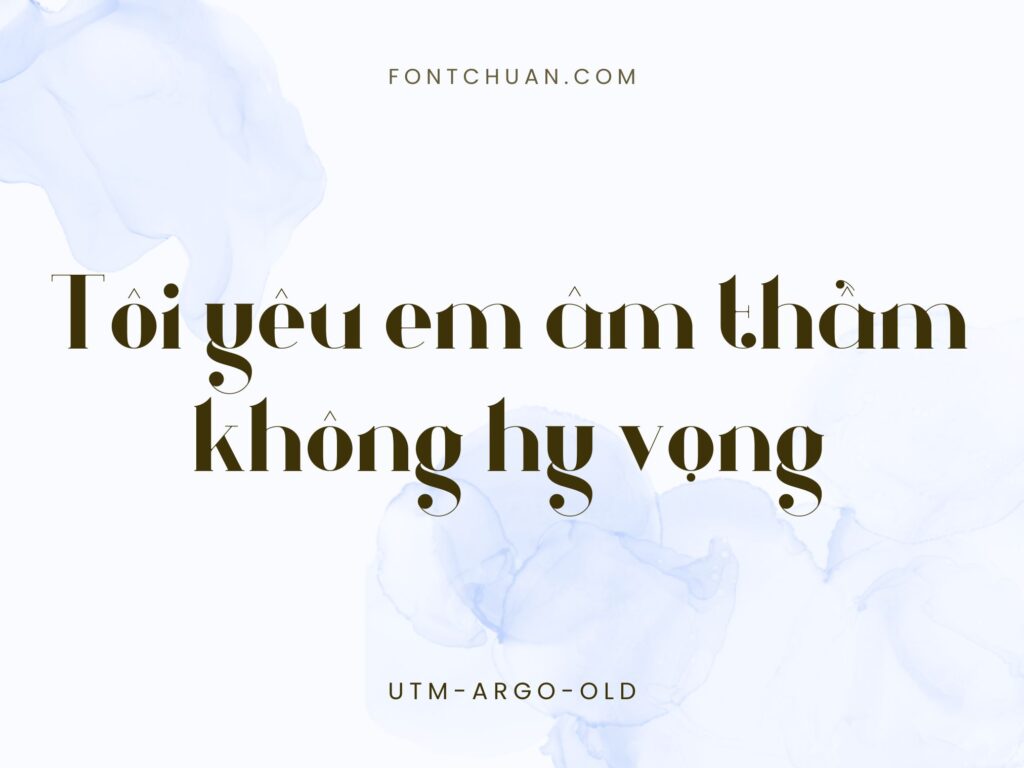
Font UTM Argo Old Việt Hóa
UTM Argo Old là một Font Serif mang phong cách cổ điển và thuộc dòng Font Vintage, được thiết kế với cảm hứng từ nghệ thuật Art Deco. Font này sở hữu các đường nét tinh tế và độc đáo, tạo nên sự sang trọng và lịch lãm trong thiết kế. Phiên bản này đã được Việt hóa bởi Đinh Kiên, hỗ trợ đầy đủ tiếng Việt cùng hơn 180 ký tự bao gồm chữ hoa, chữ thường, số, glyphs, ligatures và dấu. Đây là một trong những font được thành viên Font Chuẩn sưu tầm và chọn lọc nhằm đáp ứng nhu cầu đa dạng của bạn đọc và ứng dụng thực tế vào các dự án thiết kế.
UTM Argo Old có cấu trúc chữ với các nét thanh mảnh và chân chữ đặc trưng, mang lại cảm giác cổ điển nhưng không kém phần hiện đại. Font này phù hợp cho các ứng dụng như thiết kế logo, tiêu đề, bao bì sản phẩm, thiệp mời và các ấn phẩm in ấn khác. Các ngành nghề như quảng cáo, giáo dục, bất động sản và công nghệ có thể tận dụng UTM Argo Old để tạo điểm nhấn chuyên nghiệp và ấn tượng trong thiết kế.